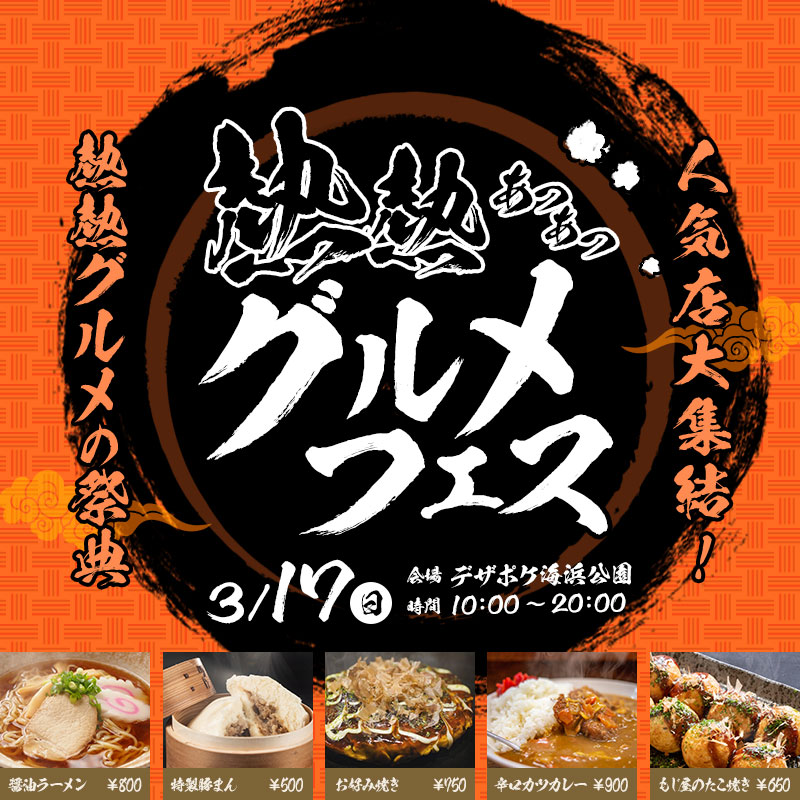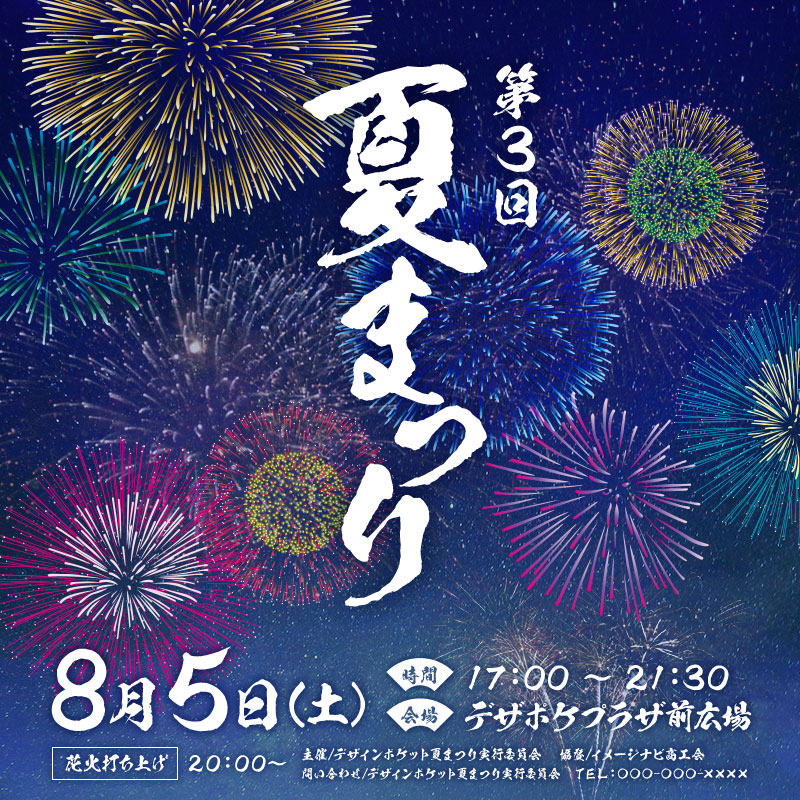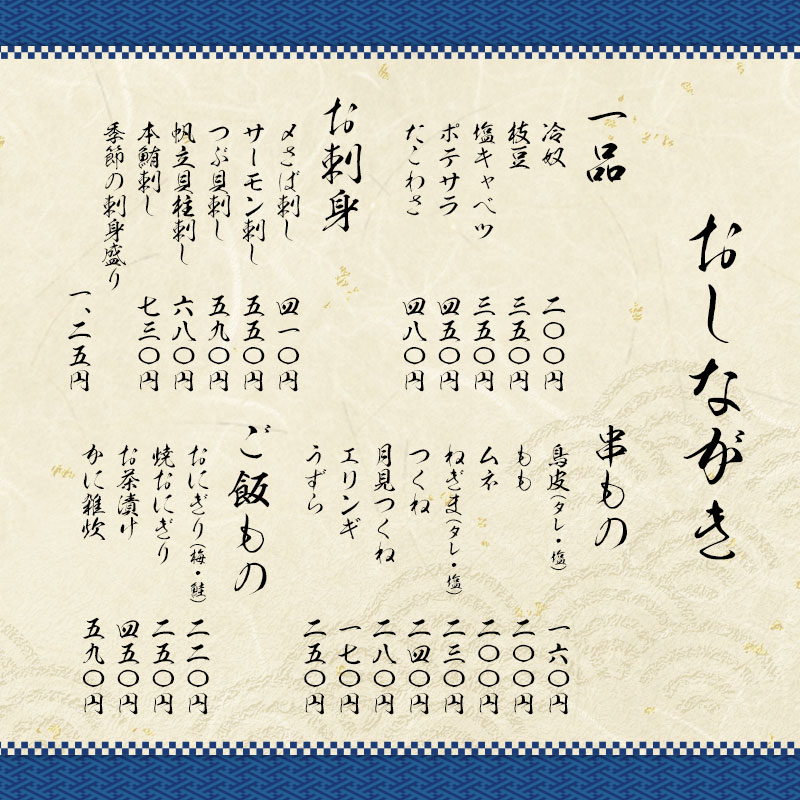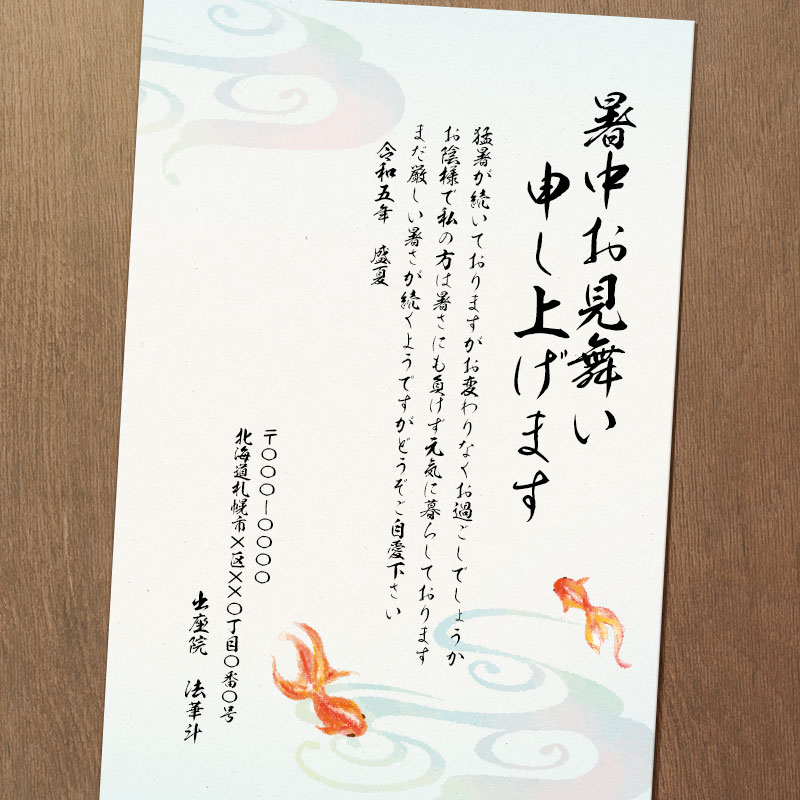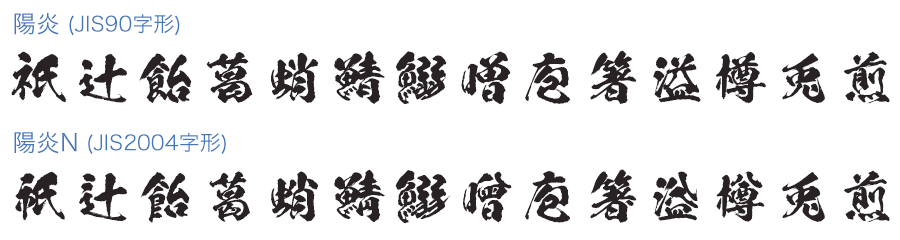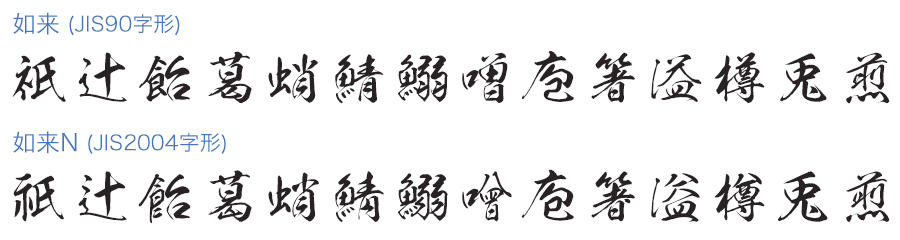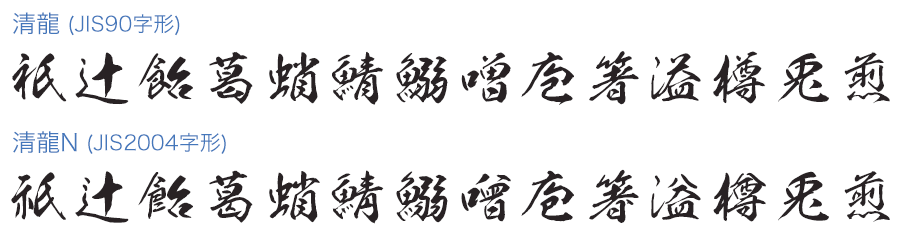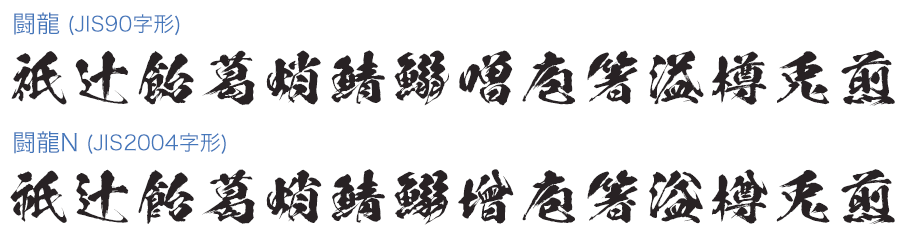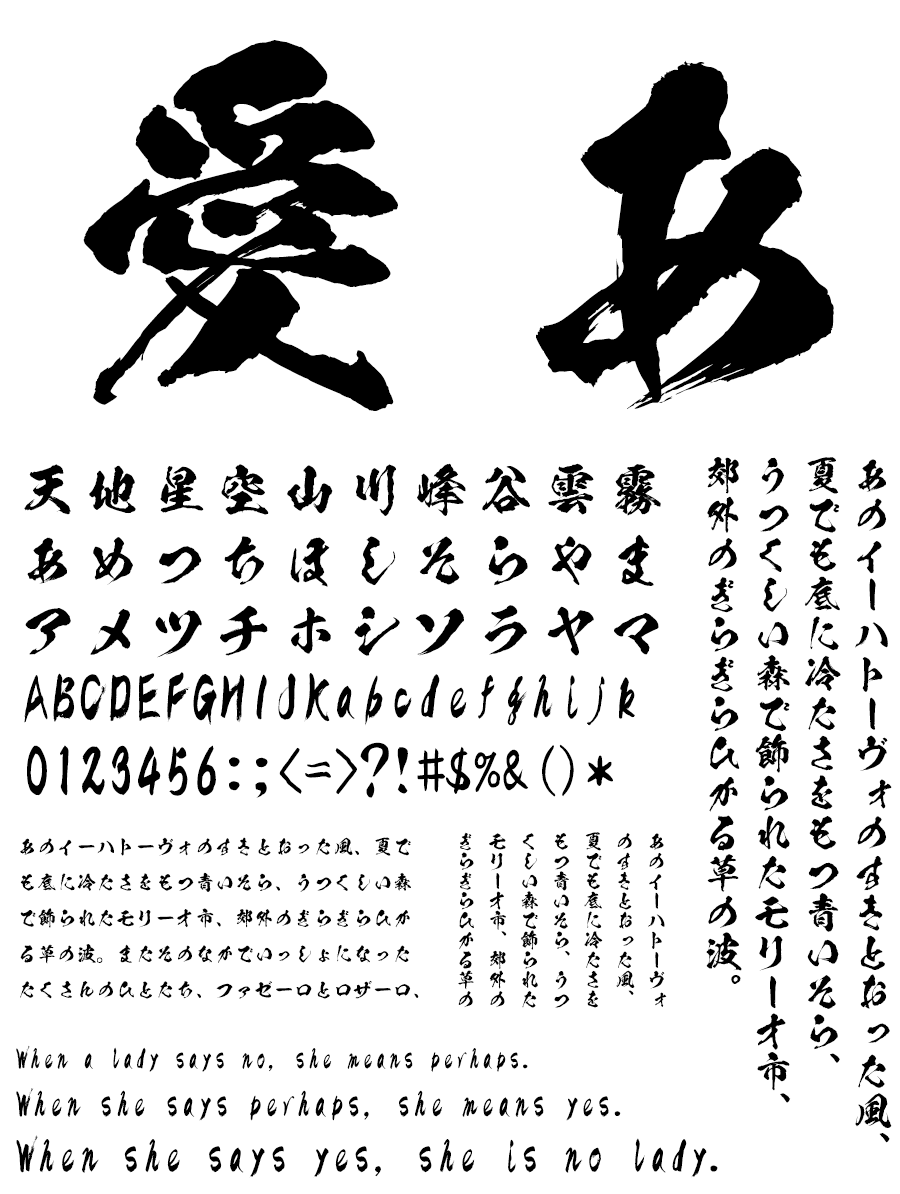
人気アニメ「鬼滅の刃」で使用された昭和書体の人気デザイン毛筆書体 闘龍書体・陽炎書体、大和撫子を思わせる細身の優しい如来書体、手紙など文章にぴったりの清龍書体の合計4書体を収録。さらにそれぞれOpenType版とTrueType版の両方を収録、用途に合わせてお使いください。
1. 闘龍書体
闘龍書体(とうりゅうしょたい)
闘争心にあふれ、力がありあまった若い龍が、空を舞うさまをイメージして作られた筆書系デザイン書体です。力強さ、荒々しさを持ちながらも、堂々と伸び渡る文字が、龍というにふさわしい、雄大なイメージを感じさせます。画線には力強い筆の運びによって生み出された大胆なかすれが残されている一方で、文字の一画一画は丁寧に描かれており、可読性が損なうことなく、インパクトのある毛筆表現を可能にしています。
2. 陽炎書体
陽炎書体(かげろうしょたい)
ゆらゆらと地を這う陽炎をイメージして作られた筆書系デザイン書体です。その名の表わすように、画線には、揺らめく炎のようなゆらぎが残っていますが、そうしたデザイン的な画線処理が施されている一方で、ほかの書体に比べて太さの変化が少なく、漢字も一画一画が丁寧に描かれています。
3. 如来書体
如来書体(にょらいしょたい)
手紙など文章を作成するにふさわしい毛筆書体です。
4. 清龍書体
清龍書体(せいりゅうしょたい)
大和撫子を思わせる細身の優しい毛筆書体です。
本格毛筆書体ブランド 昭和書体 とは?
昭和書体は、あらゆる使用目的にマッチする毛筆書体の提供を目指し、揮毫職人が1文字1文字丁寧に書き上げた本格毛筆書体ブランドです。
昭和書体の特徴
書家「綱紀栄泉」が1文字1文字丁寧に書き上げた筆文字
昭和書体の多くの書体を手掛けてきた書家「綱紀栄泉 (つなのりえいせん)」。1人の書家が64種類もの形態の異なる毛筆書体を書き上げた例を他に見たことがありません。1つの書体には第一水準から第二水準までの約7,000文字が必要で、64書体に書き分けた文字は約50万字。書き直しを含めると2倍近くにものぼる気の遠くなる作業です。まさに奇人であり天才と言う他なく、現代の弘法大師と呼べる存在です。奇しくも紫雲山上宮寺 (しうんざんじょうぐうじ) という寺の長男として生まれている事も、何らかの仏縁を感じざるを得ません。昭和10年生まれの高齢ながら精力的に活動されていましたが、2022年3月惜しまれながらも他界されました。
現在は御子息の坂口茂樹氏が二代目栄泉としてその遺志を引き継ぎ、鋭意揮毫中です。